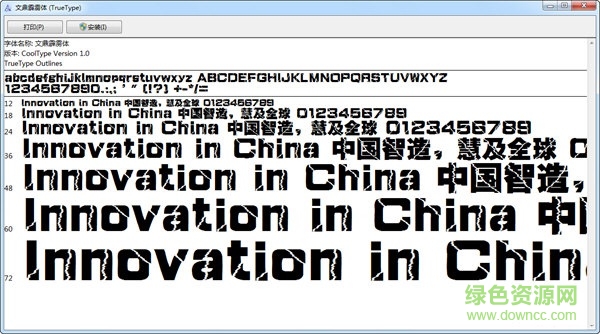
pilieg ultra gb
pilieg ultra gb字体是文鼎霹雳体的英文名称,这是一款非常自带撕裂效果的文鼎字体,可以给文字增添闪电效果,看上去霸气十足,欢迎下载!
piliegultragb字体特点
该字体最大的特点在于,破裂效果非常明显,更能彰显裂痕体的字形效果,对于设计师们来说,应该经常会用到。